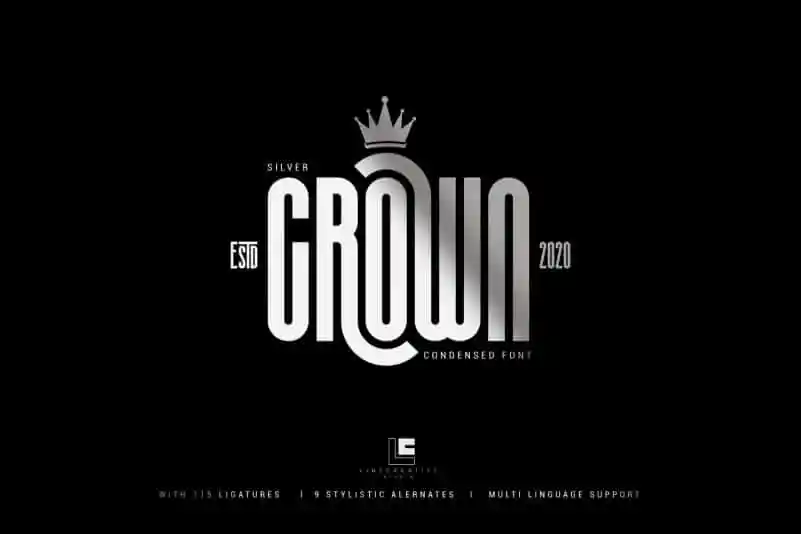
Silver Crown – Condensend Font – Download Grátis
Silver Crown – Condensend Font é uma elegante escolha para designers que buscam um estilo moderno e minimalista. Inspirado no título “Ultra Condensend”, essa fonte traz uma simplicidade incomparável, com seus caracteres compactos e agradavelmente espaciados. Ideal tanto para projetos de identificação visual como logomarcas ou cards de visita, quanto para layouts ambiciosos em revistas ou grande escala, ou até mesmo trabalhos impressos em superfícies frágeis, como ovens queimadores. Seu design minimalista e sua disposição perfeita criam um impacto instantâneo que se adequa a uma variedade de usos, desde aplicativos digitais até gráficos tradicionais. É perfeito para qualquer projeto que exija estilo moderno e eficaz.